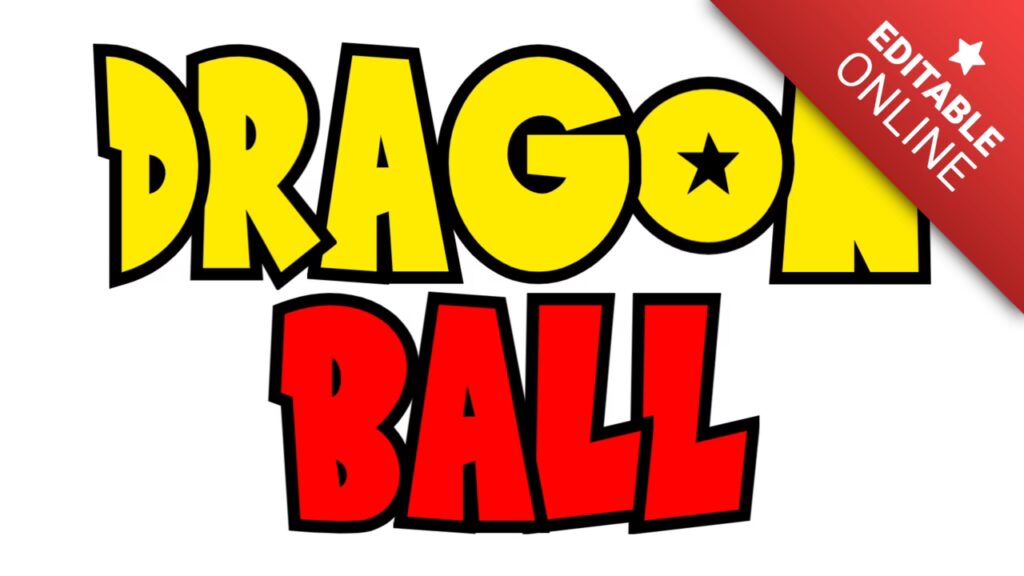
El universo de Dragon Ball Z no solo nos ha regalado batallas épicas, transformaciones inolvidables y personajes que han marcado a generaciones, sino también una estética visual inconfundible. Uno de sus elementos más reconocibles es su tipografía: angular, enérgica y llena de poder. Ver esas letras es transportarse instantáneamente a un mundo de Kamehamehas y Super Saiyans. Si alguna vez has querido capturar esa esencia para tus propios proyectos, ya sea para un banner de YouTube, una miniatura, un fondo de pantalla o simplemente por diversión, has llegado al lugar indicado. En esta guía completa, te mostraremos paso a paso cómo crear tus propios gráficos de texto con el estilo de la fuente de Dragon Ball Z, explorando desde las herramientas más sencillas hasta los métodos más profesionales.
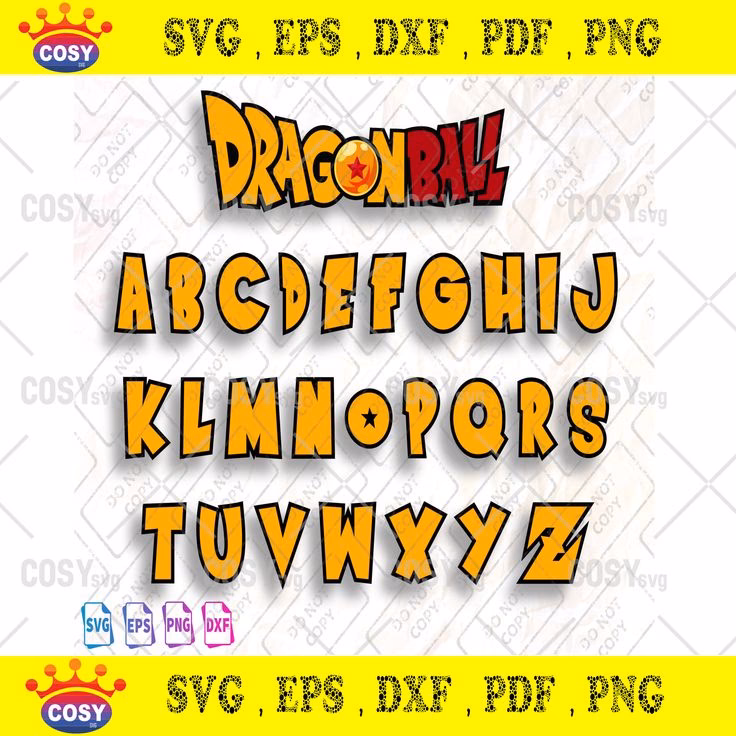
¿Existe una fuente oficial de Dragon Ball Z?
Antes de sumergirnos en el cómo, es importante aclarar un punto clave. No existe una única fuente oficial llamada "Dragon Ball Z Font" que puedas descargar e instalar como si fuera Arial o Times New Roman. El logotipo y los títulos que vemos en la serie fueron diseñados a medida, son piezas de arte gráfico. Sin embargo, la comunidad de fans, con su increíble talento y dedicación, ha creado fuentes que imitan este estilo a la perfección. La más famosa y utilizada es, sin duda, Saiyan Sans. Esta fuente captura la esencia de las letras angulares y dinámicas que todos asociamos con la saga de Akira Toriyama, y será la base para la mayoría de los métodos que exploraremos.
Método 1: Generadores de texto en línea (La vía rápida)
La forma más sencilla y accesible de crear un texto con el estilo de Dragon Ball Z es utilizando un generador en línea. Estas herramientas web te permiten escribir tu texto, personalizar algunos aspectos y descargar el resultado como una imagen, todo sin necesidad de instalar ningún software.
¿Cómo funcionan?
Estos sitios web tienen preconfigurada la fuente estilo DBZ (generalmente Saiyan Sans) y una serie de efectos visuales. Tú simplemente sigues unos pasos sencillos:
- Paso 1: Encuentra un generador: Realiza una búsqueda en tu navegador con términos como "generador de fuente Dragon Ball Z" o "Dragon Ball Z text generator". Encontrarás múltiples opciones disponibles.
- Paso 2: Introduce tu texto: Localiza el campo de texto en la página y escribe las palabras que quieres transformar. Por ejemplo, "Super Guerrero" o el nombre de tu canal.
- Paso 3: Personaliza el diseño: Aquí es donde ocurre la magia. La mayoría de los generadores ofrecen opciones para modificar:
- Tamaño de la fuente: Ajusta qué tan grande o pequeño quieres tu texto.
- Color del texto: Elige el color de relleno principal. Para un look clásico, opta por un amarillo o naranja intenso.
- Color del borde (Stroke): Este es un detalle crucial. La tipografía de DBZ casi siempre tiene un borde grueso. Los colores más comunes son el rojo o un azul oscuro.
- Sombra: Añadir una sombra paralela puede darle profundidad y hacer que el texto resalte aún más.
- Estilos y efectos: Algunos generadores más avanzados pueden ofrecer efectos de degradado, texturas o incluso fondos temáticos.
- Paso 4: Genera y descarga: Una vez que estés satisfecho con el resultado, busca un botón que diga "Generar", "Crear" o similar. La herramienta procesará tu solicitud y te mostrará una vista previa. Si te gusta, podrás descargarla como un archivo de imagen, comúnmente en formato PNG con fondo transparente, lo cual es ideal para superponerlo sobre otros diseños.
Ventajas y desventajas de los generadores en línea
Aunque son muy prácticos, es importante conocer sus pros y sus contras.
- Ventajas: Son extremadamente fáciles de usar, rápidos y no requieren conocimientos técnicos ni instalación de programas. Son perfectos para creaciones puntuales y rápidas.
- Desventajas: La personalización es limitada a las opciones que ofrece el sitio. El resultado es una imagen rasterizada (basada en píxeles), lo que significa que si la agrandas demasiado, perderá calidad y se verá pixelada. Además, algunos sitios pueden incluir pequeñas marcas de agua.
Método 2: Instalar la fuente en tu ordenador (El camino del profesional)
Si buscas control total, máxima calidad y la capacidad de integrar el texto en proyectos más complejos, la mejor opción es descargar e instalar la fuente en tu sistema operativo. Esto te permitirá usarla en programas de diseño gráfico como Adobe Photoshop, GIMP (una alternativa gratuita), Affinity Designer, e incluso en editores de video o documentos de texto.
Paso a paso para la instalación:
- Descargar la fuente: Busca "descargar fuente Saiyan Sans". La encontrarás en numerosos repositorios de fuentes gratuitos. Asegúrate de descargarla de un sitio web de confianza. Las fuentes suelen venir en un archivo comprimido (.zip).
- Descomprimir el archivo: Haz clic derecho sobre el archivo .zip y selecciona "Extraer todo". Dentro de la carpeta extraída, encontrarás los archivos de la fuente, que suelen tener extensiones .TTF (TrueType Font) o .OTF (OpenType Font).